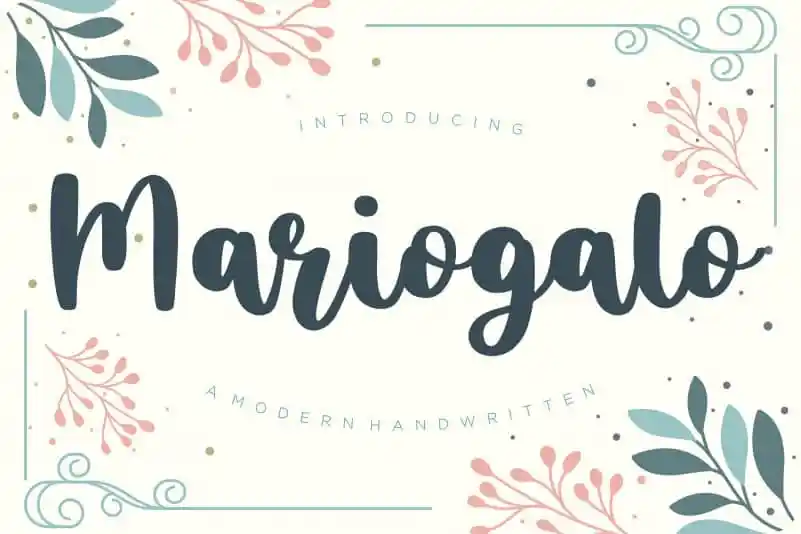
Mariogalo Modern Handwritten Font
A Mariogalo Modern Handwritten Font oferece uma experiência visual única que é perfeita para expressar sentimentos suaves e emotivos. Suas linhas fluidas e desenhadas ao vivo fornecem um toque elegante aos seus projetos, seja em embalagens de produtos, identidades corporativas, revistas, redes sociais, casamentos ou qualquer outro tipo de projeto que precise de uma pitada de personalidade. Com sua graça natural e delicadeza, essa fonte é ideal para expressar mensagens com um toque elegante e suave. Não importa o contexto do seu trabalho, a Mariogalo Modern Handwritten Font traz uma atmosfera envolvente e natural que certamente destacará seus projetos em qualquer situação.